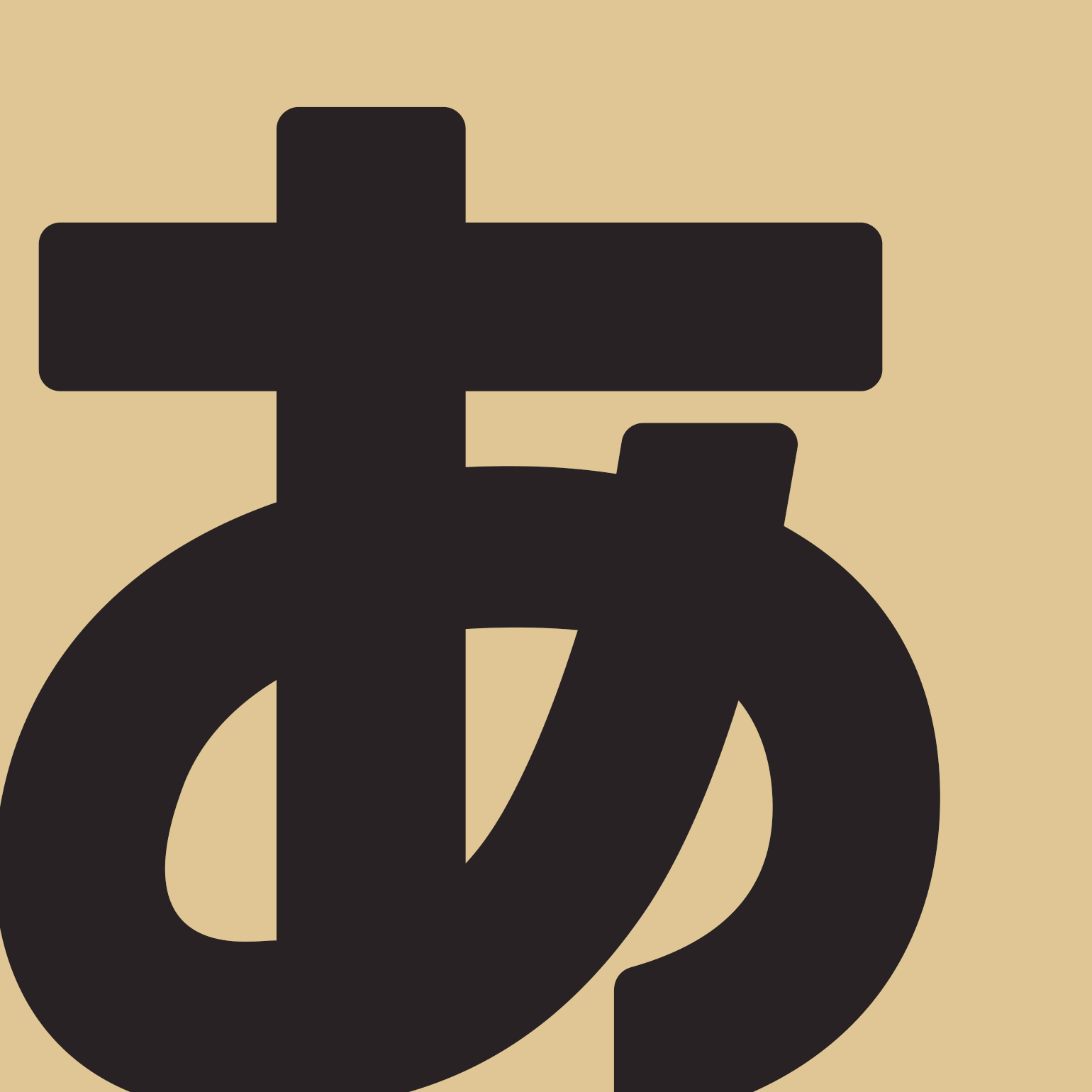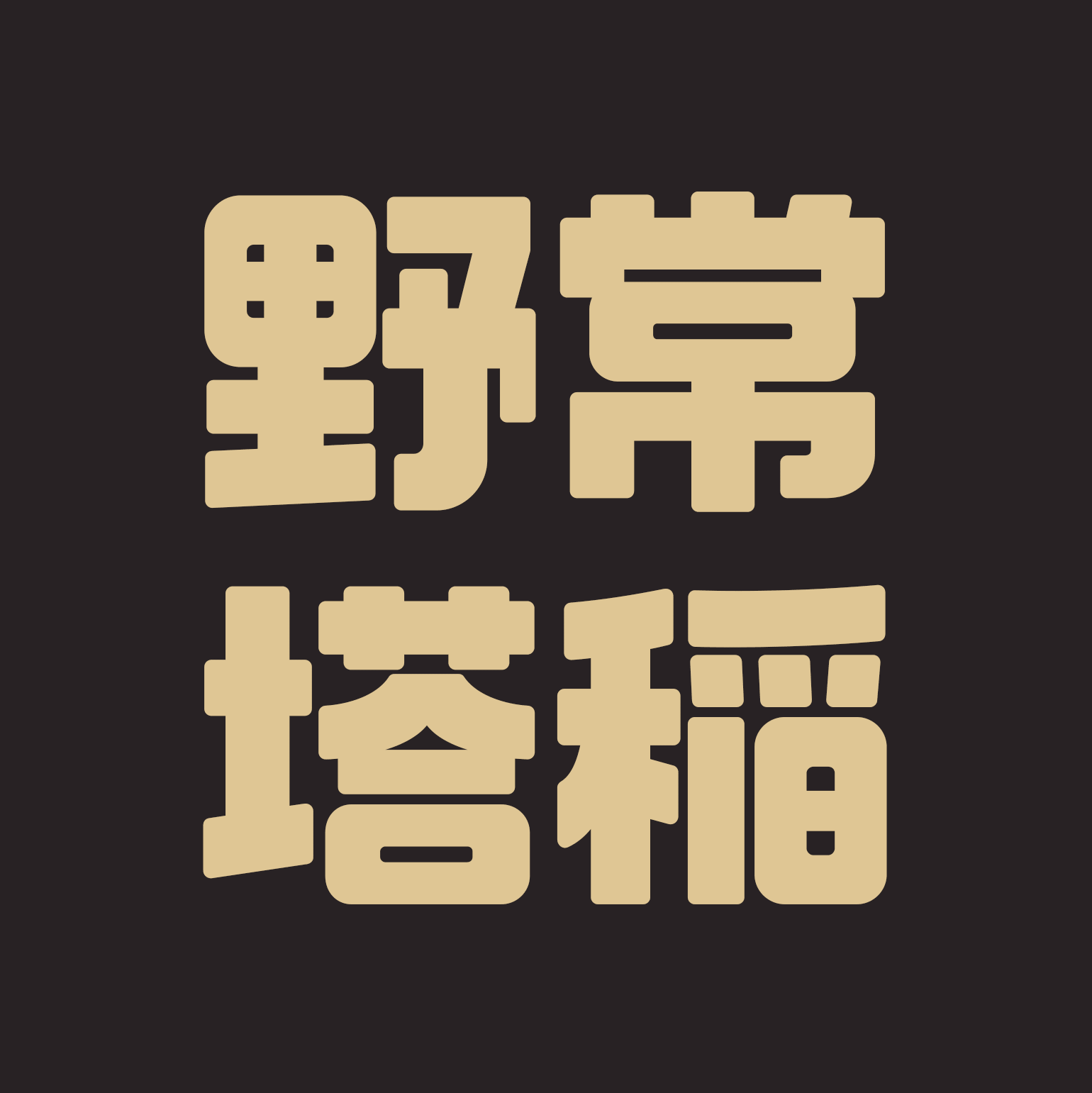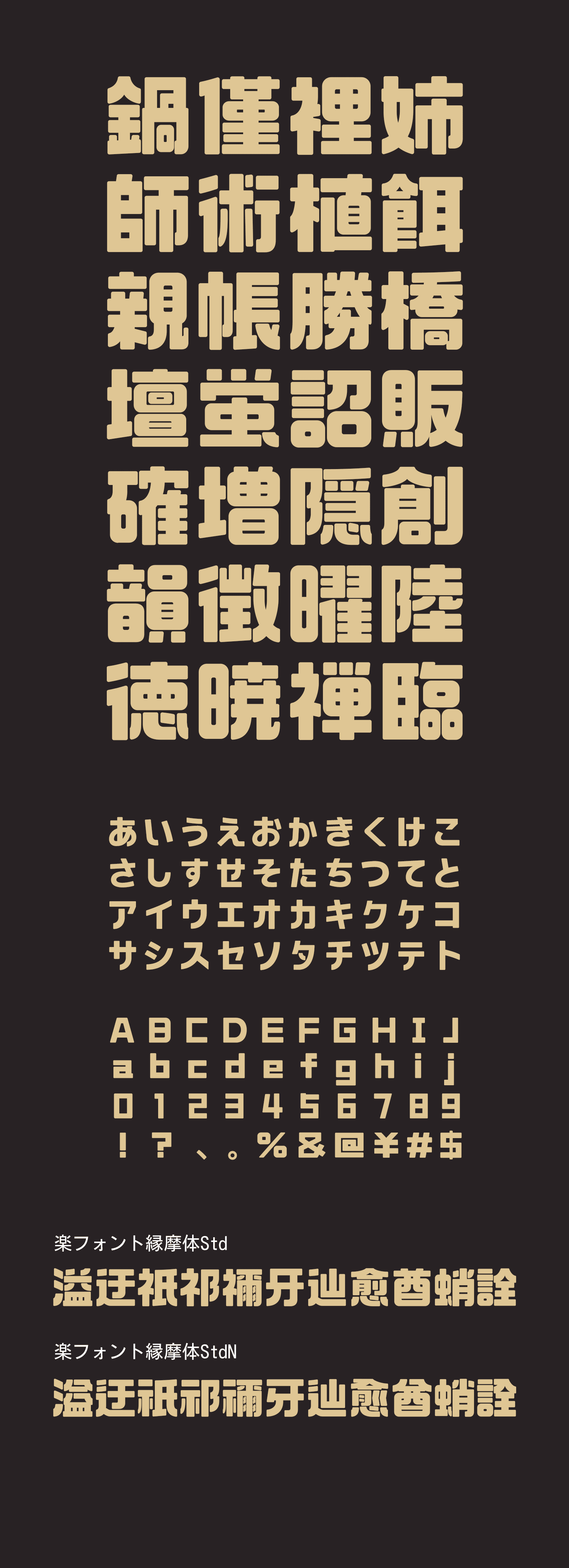
縁摩体(えんまたい)
少し丸く落とした角は、人の賑わう街の中で生きる文字が時を経て摩耗し、丸くなったような風情を演出しています。 時間が経ってもなお、個性的な存在感を放てるようなウエイトは、冥界の王である閻魔様のように骨太な印象を与えますが 楽フォントの技巧によりしっかりとした骨組みのもとで設計されているため、複雑な漢字もしっかりと可読性を保っています。 街の雑踏のような、多くの要素の中に馴染みながらも、はっきりとした主張・イメージを残せる書体です。